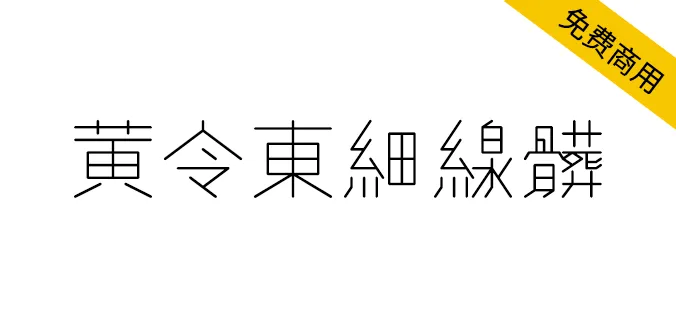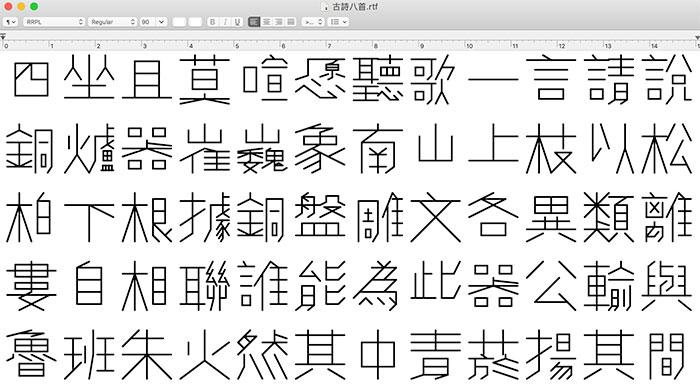
黃令東細線體( RRPL),由程序自動生成,用遞歸根式包裝語言(RRPL)進行編寫。在RRPL中,每個漢字被描述為數字、符號和對其他字符的引用的短字符串。它的語法靈感來自標記語言,如乳膠(LaTeX,一種基於ΤΕΧ的排版系統),以及傳統的用於書法練習的“米”網格。使用5000+的繁體漢字和詞根,其字形由默認解析器生成,由於是程序自動生成的字體,所以難免會有錯別字,使用時要注意檢查。
需要注意的是,由於是繁體的詞根,所以輸入簡體字的話會直接映射成繁體字形。比如說你輸入“國”字,會被成繁體的“國”字。